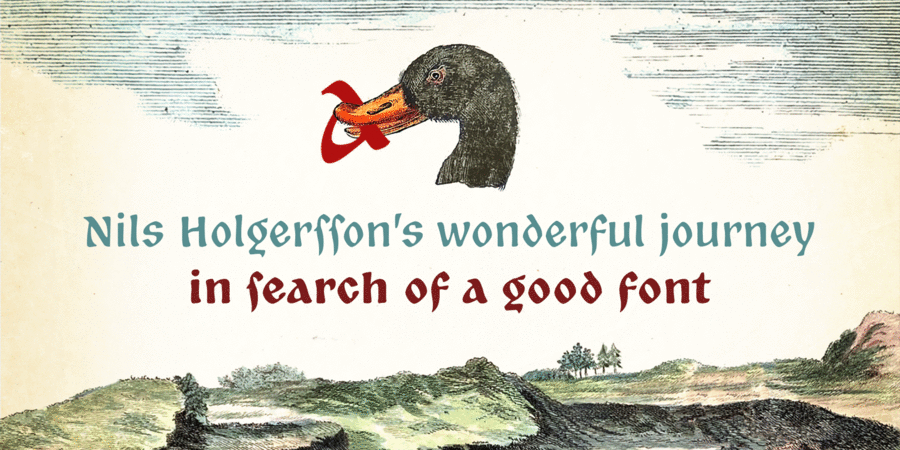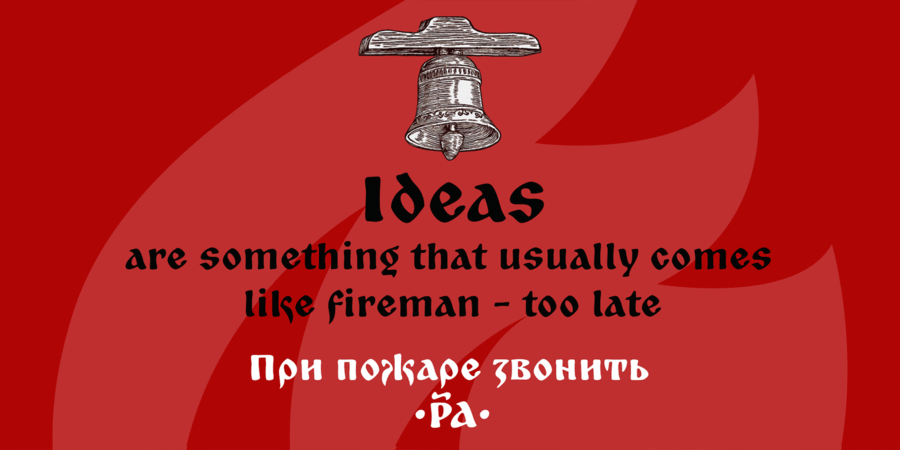
Опис гарнітури ZaharШрифт Zahar, зроблений на базі оцифровки написів, що їх створив свого часу видатний український графік Георгій Якутович для оформлення відомого твору Івана Франка. Цей шрифт акцидентний, з явними ознаками стилізованого давньослов’янського письма з ухилом до народних казок, пісень тощо. Завдяки м’якому контуру та значній насиченості природньо трансформується за пропорцями, нахилом тощо. Добре пасуватиме для оформлення дитячих книжок та інших подібних матеріалів. Містить стандартну кирилку (слов’янські мови) та європейську латинку, може бути розвинутий у будь-який бік за накресленнями, мовами, писемними системами тощо. Шрифт розробили Генадій Заречнюк та Віктор Харик за мотивами літерації Георгія Якутовича у 2011–2019 роках.
Асоціації з сімейством шрифтів ZaharОсобистість і характер гарнітури:
плоскінний, сірмяжний, сільський, релігійний, церковний, православний, крафтовий, мужній, динамічний, оригінальний, вільний, пластичний, етнічний, природний, натуральний, традиційний, героїчний, старовинний, козацький, вольний, колоритний, живий, темпераментний, органічний, грунтовий, народний, наївний, неохайний, древній, тайговий, пташиний, берестяний, лубочний, лісовий, характерний, селянський, провінційний, самобутній, неординарний, хенд мейд, кустарний, бабусин, казковий, епічний, зелений, екологічний, старовірський, язичницький, неформальний, М'який, фермерський, домашній, літній, архаїчний, рослинний, дерев'яний, рукотворний, консервативний, дикий, добрий, надійний, історичний, племінний, артізанальний, біблійний, християнський, сакральний, різдвяний, сильний